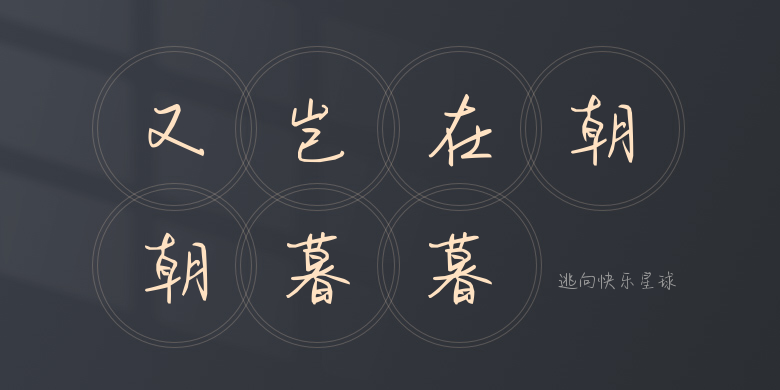
逃向快乐星球
逃向快乐星球,这款字体结构工整、笔画清晰,兼顾美观与易读性,适用于标题、正文、海报、包装、LOGO 等多种场景。字形优雅稳定,风格百搭耐看,适配日常排版与创意设计,让文字呈现更舒适、更具质感。逃向快乐星球一笔一画,皆是细节,以均衡的比例、流畅的线条打造舒适视觉体验,字形端正大气,风格简约现代。无论是商业设计、品牌宣传还是日常排版,都能轻松驾驭,让文字更有格调与力量。逃向快乐星球字体下载。